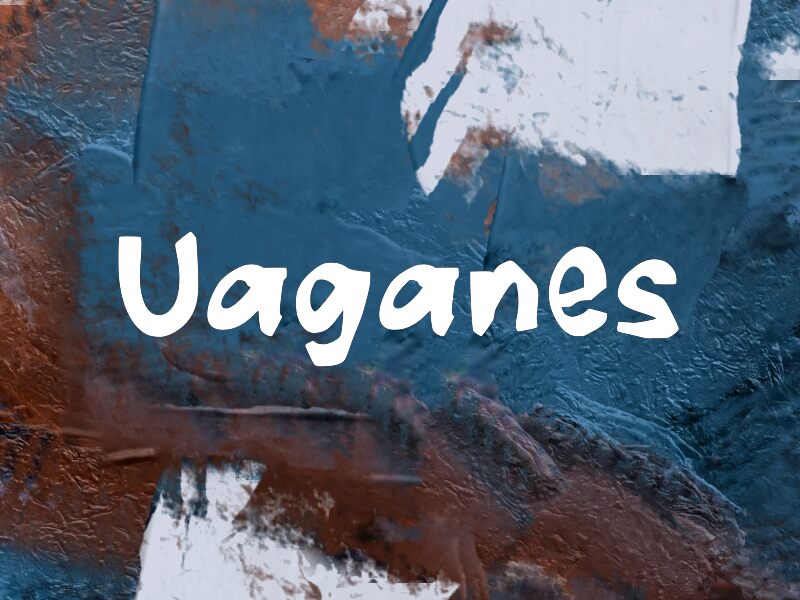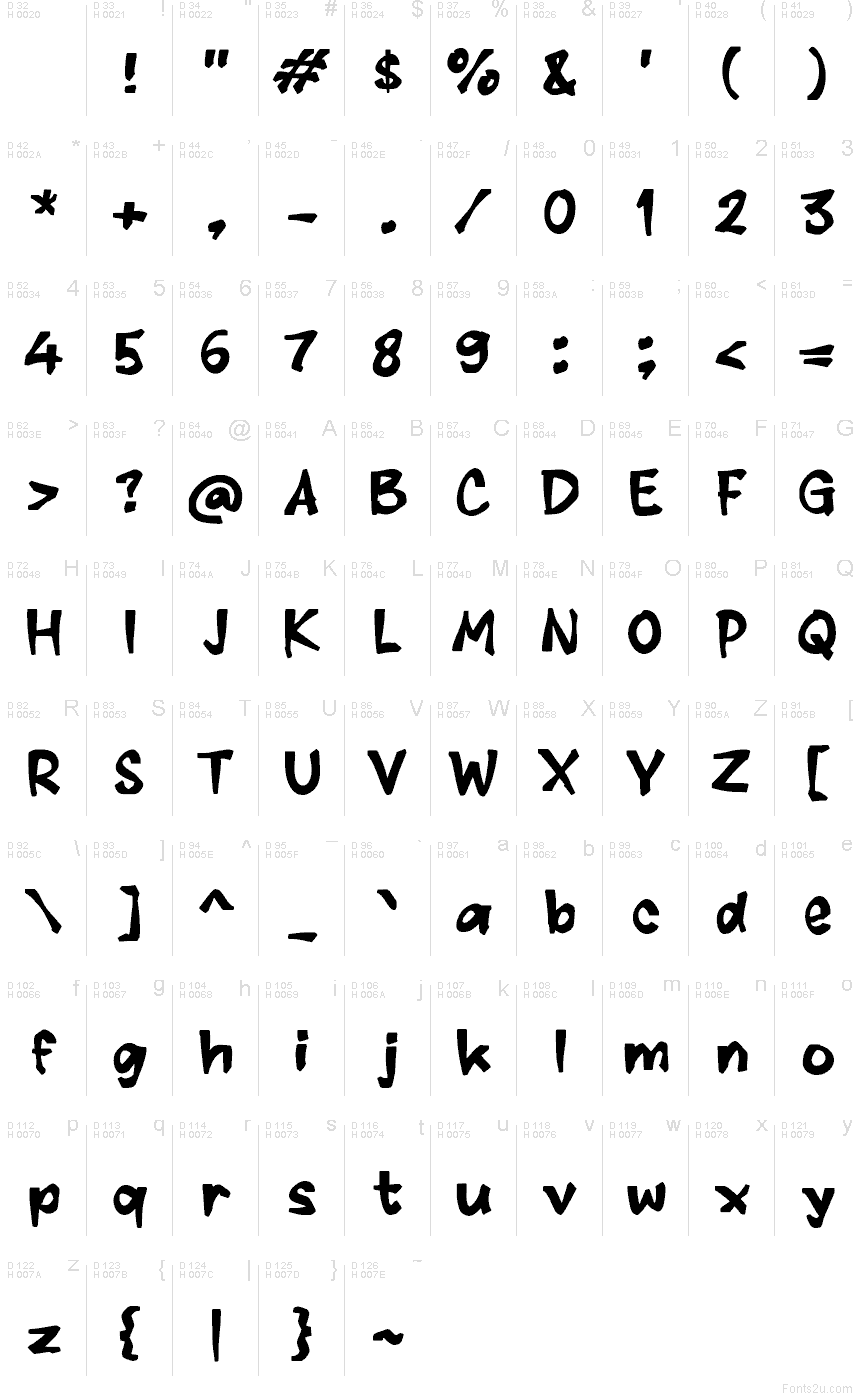
Uaganes, criada por Wep, é uma fonte de graffiti gratuita com uma vibe descontraída de arte urbana. As letras são espessas e têm um dinamismo próprio, com curvas arredondadas, extremidades cortadas e um ritmo levemente irregular que confere ao visual um aspeto de pintura rápida, em vez de algo desenhado mecanicamente numa grelha.
É por isso que esta fonte gratuita se encaixa perfeitamente em cartazes, flyers de música, branding de streetwear, fanzines de skate e títulos impactantes onde uma tipografia de estúdio demasiado polida pareceria demasiado limpa. Também funciona muito bem em títulos e cabeçalhos curtos, uma vez que os traços pesados e as curvas suaves dão energia e personalidade, mesmo a palavras curtas.
Uaganes